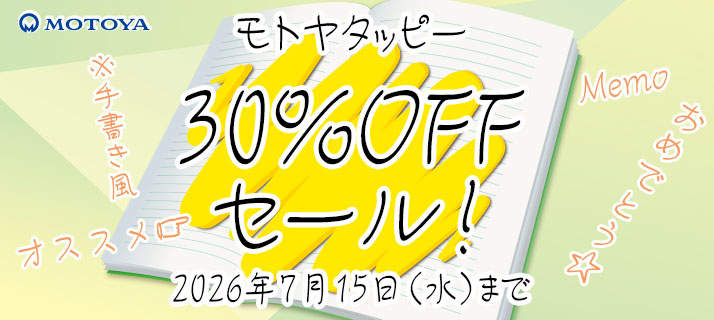
モトヤタッピーは、ボールペンなどで少し急いで書いたような、書き崩れた文字が特徴の手書き風書体です。
制作においては、クラスメイトから借りた授業ノートに書かれていそうな「ラフだけど親しみやすい」「上手すぎず、下手すぎない」「整っていないけど読める」、そんな身近な文字を目指しました。
書体名は、「下手(へた)っぴ」でもあり「達筆(たっぴつ)」でもあることから「タッピー」と名付けました。